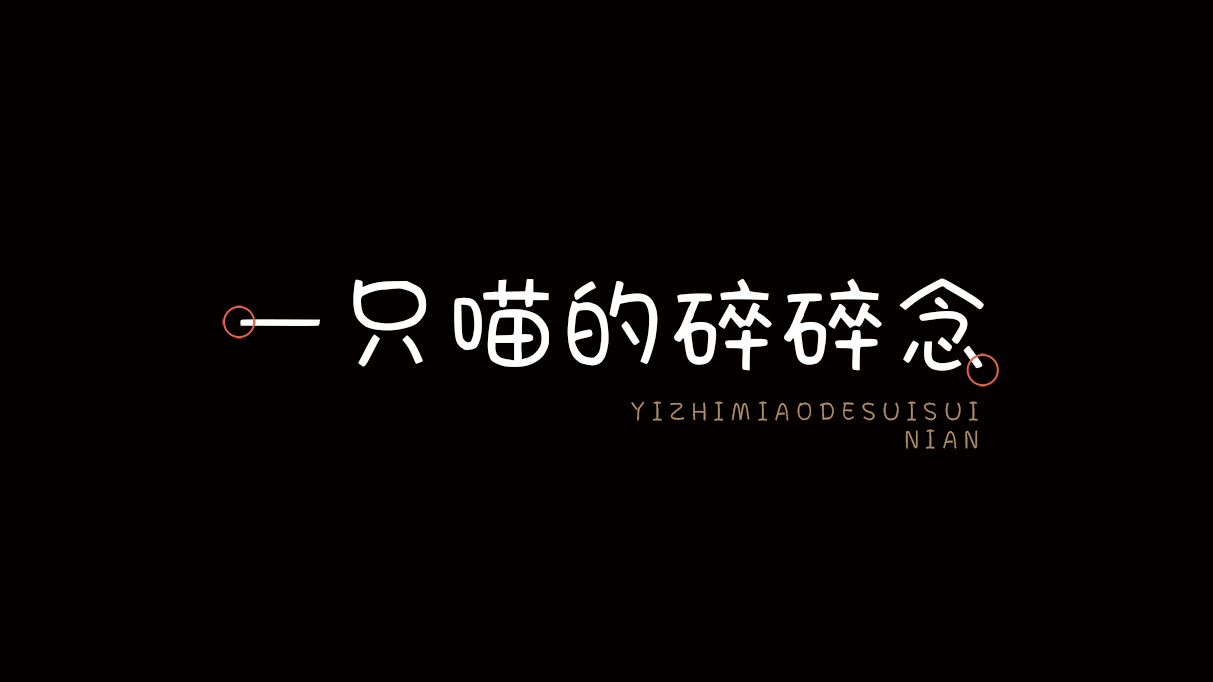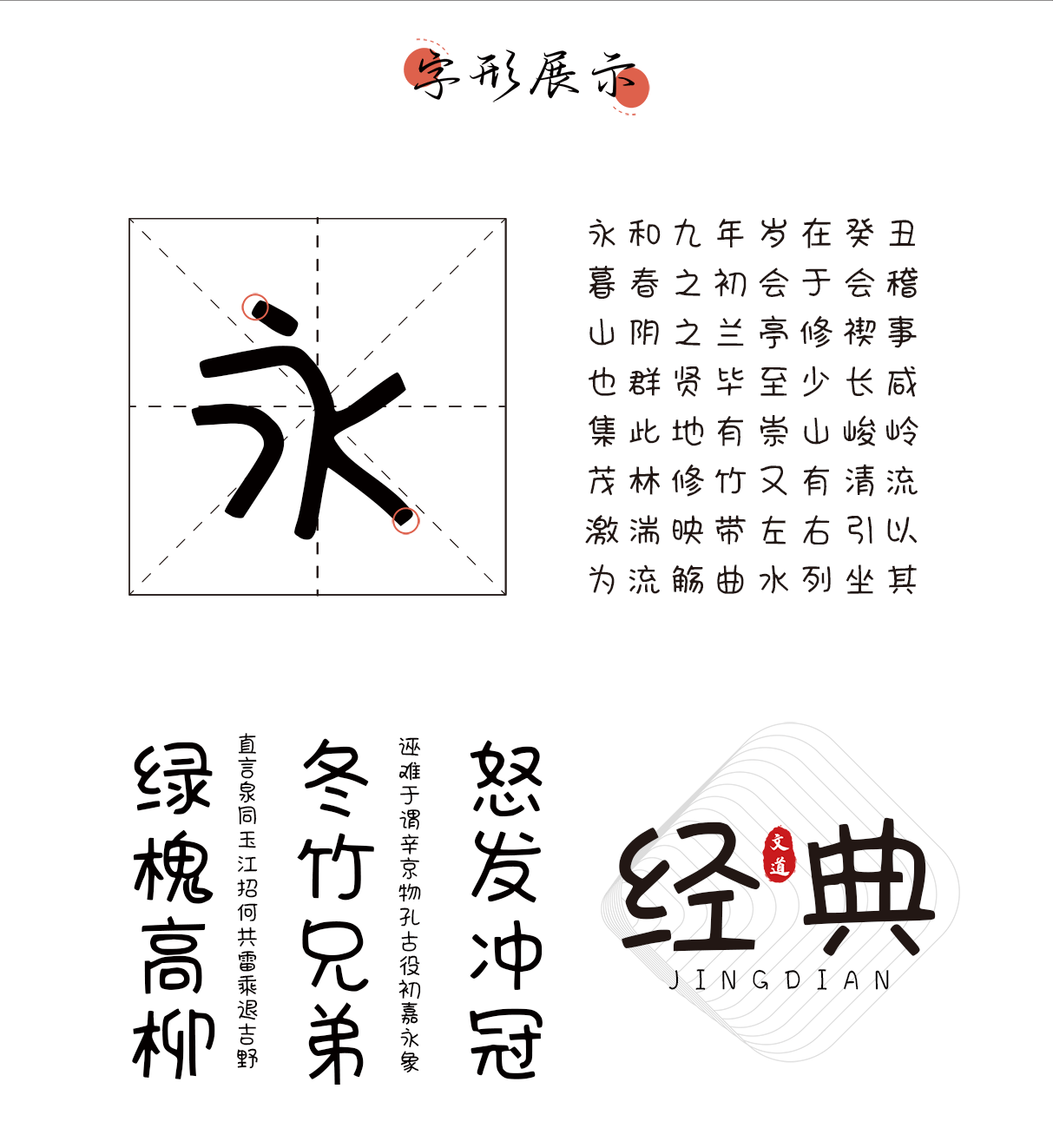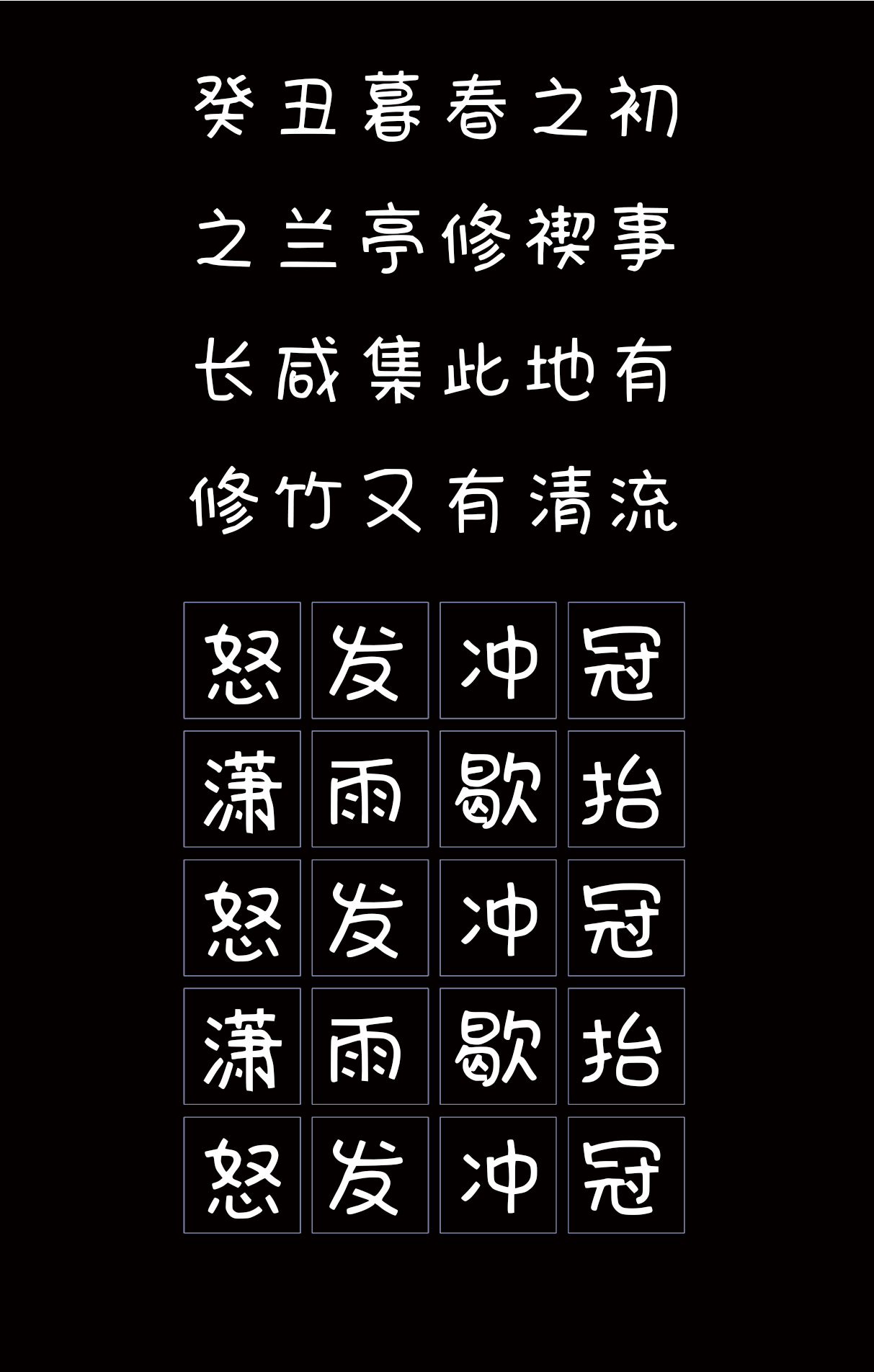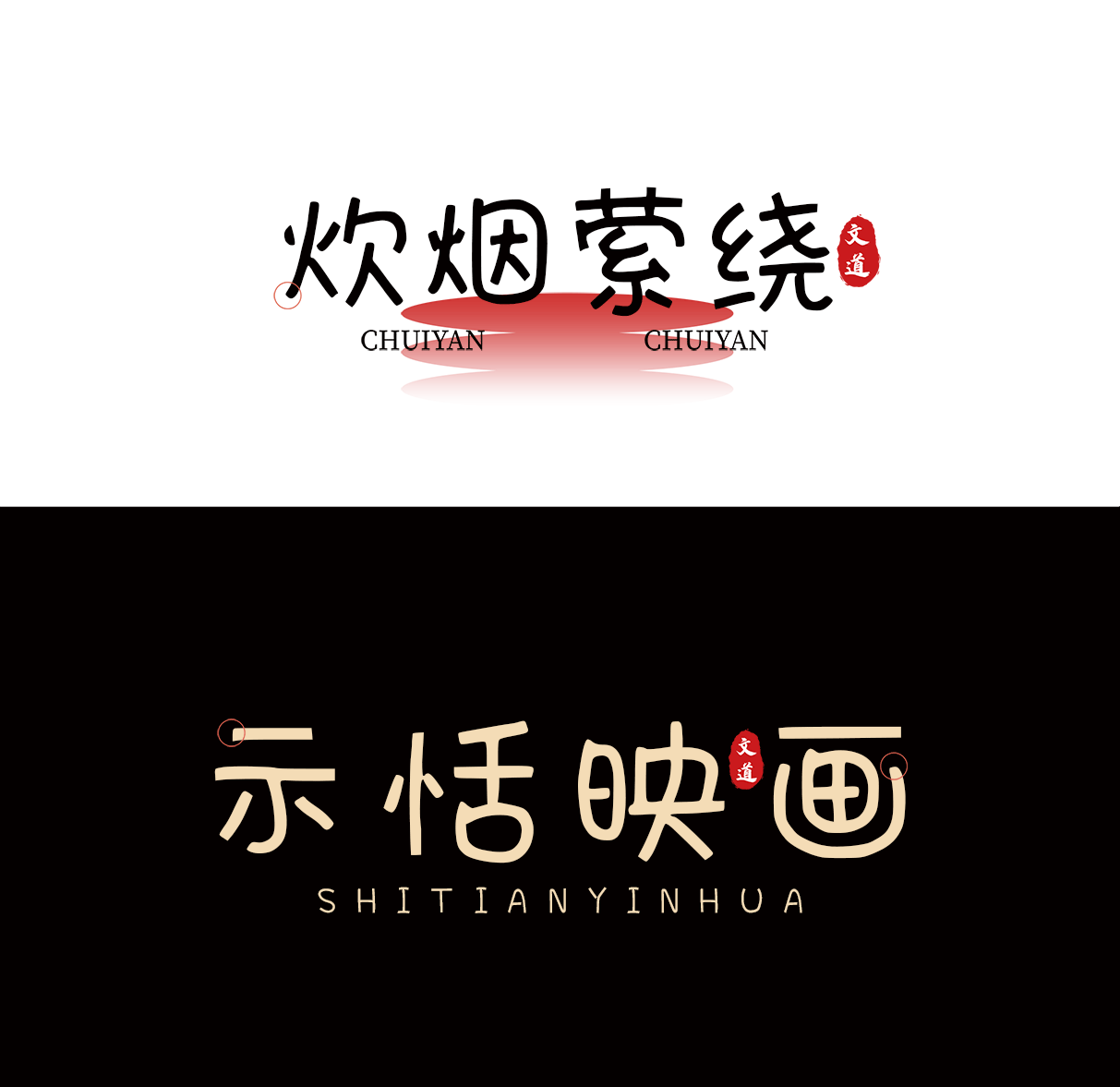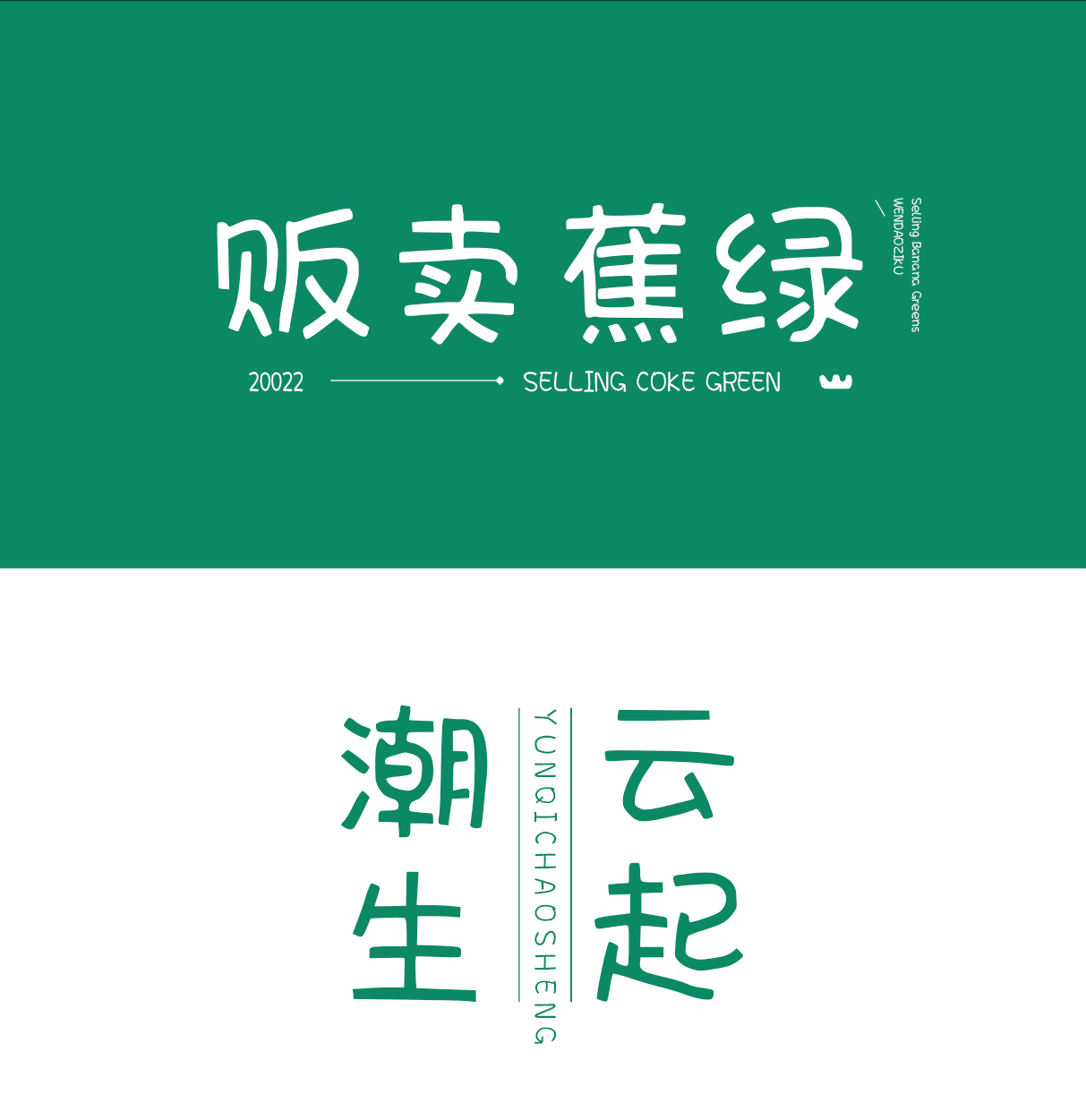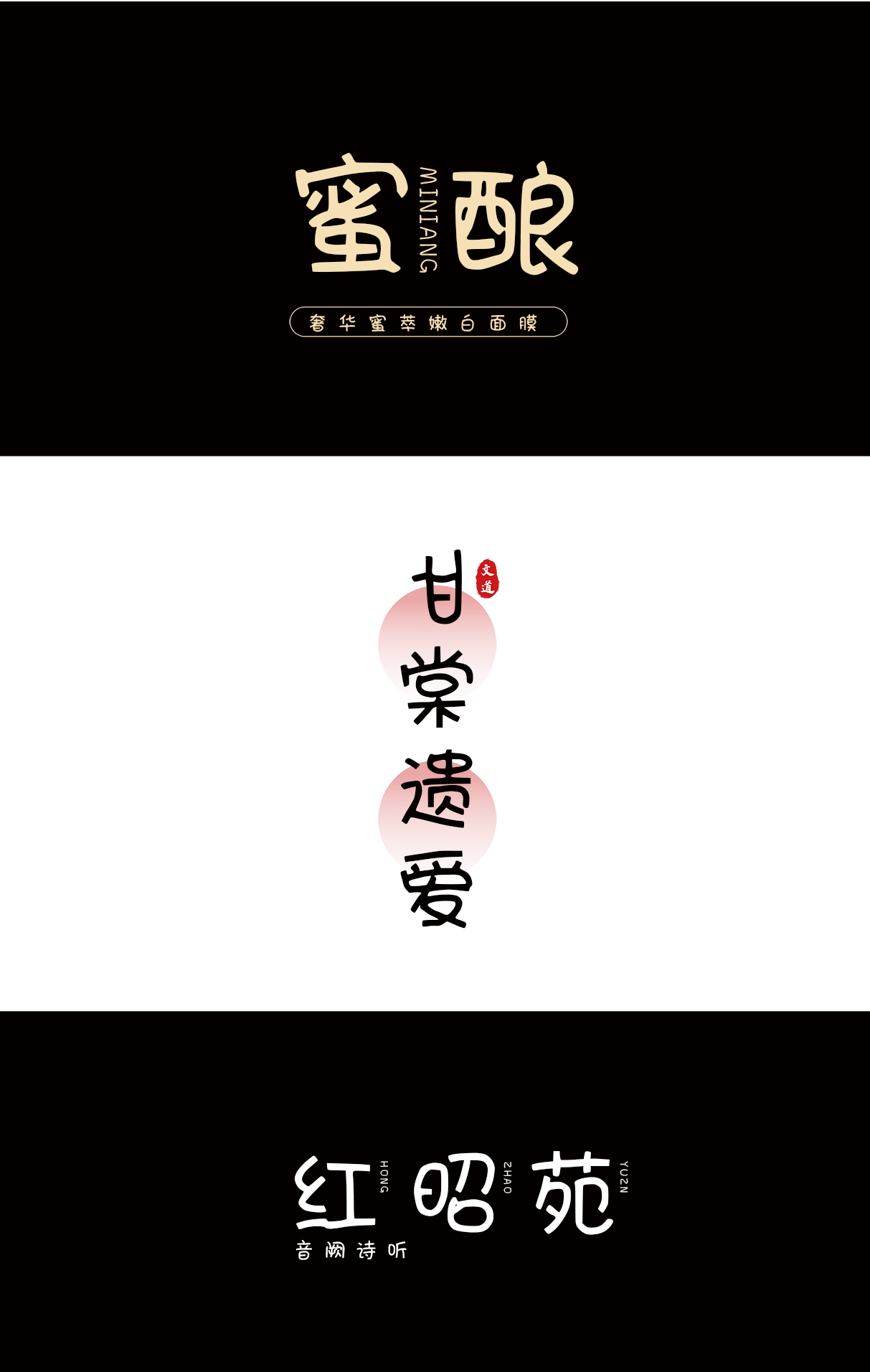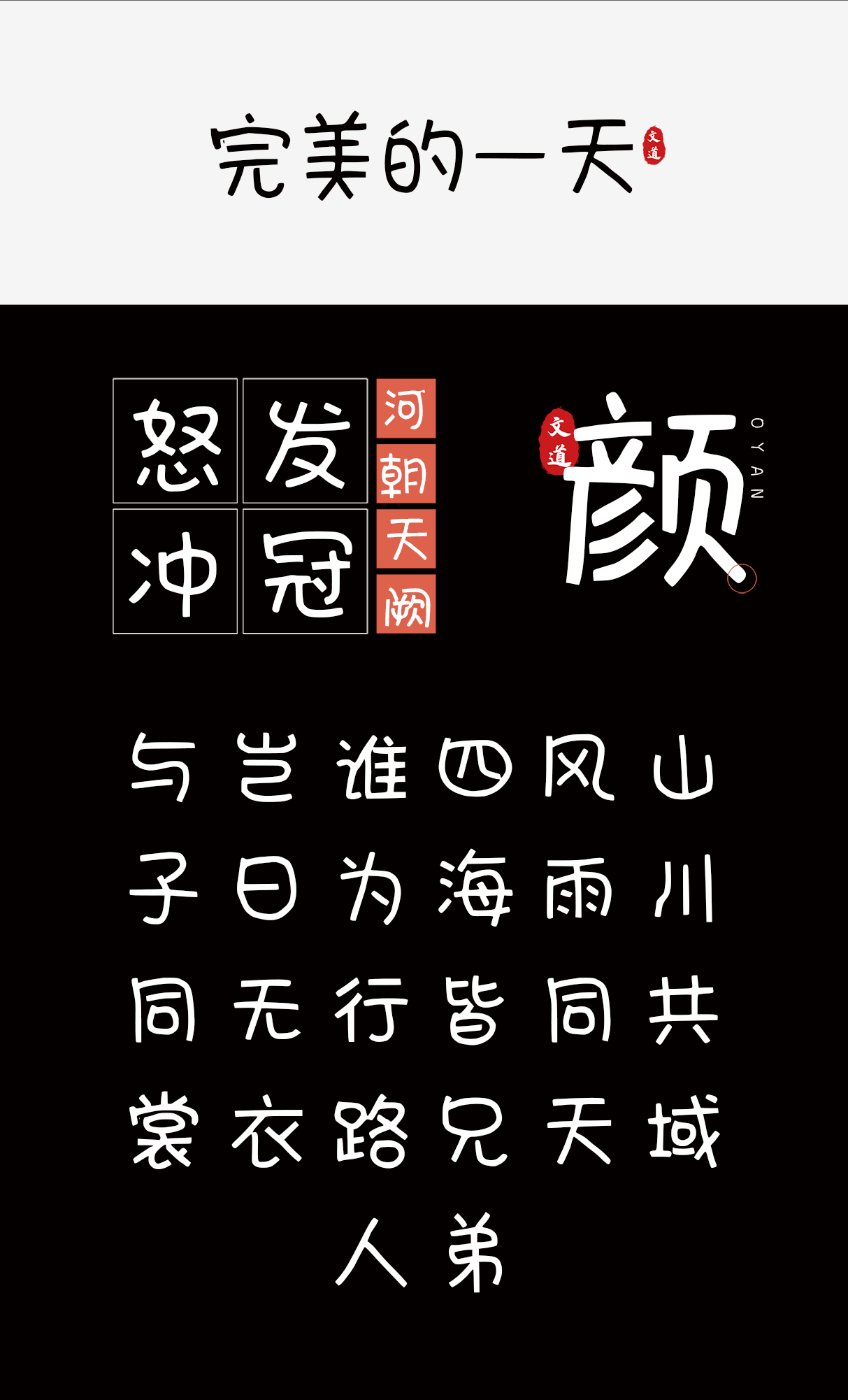
| 字体名称: | 一只喵的碎碎念 |
| 所属分类: | 创意体 可爱 圆体 |
| 简介: | 一只喵的碎碎念是一款POP风格的创意字体。这款字体的笔形由单线条构成,无多余装饰,以手绘简笔卡通的方式来呈现汉字结构,比如口字形简化为手写圆圈,字面和重心相对一致,具有一定的易读性。一只喵的碎碎念的个性天真无邪,活泼可爱。不但适用于儿童类的书刊、品牌广告和产品包装设计,以及社交网络的个性化用字,还可胜任简短的正文排版。 |